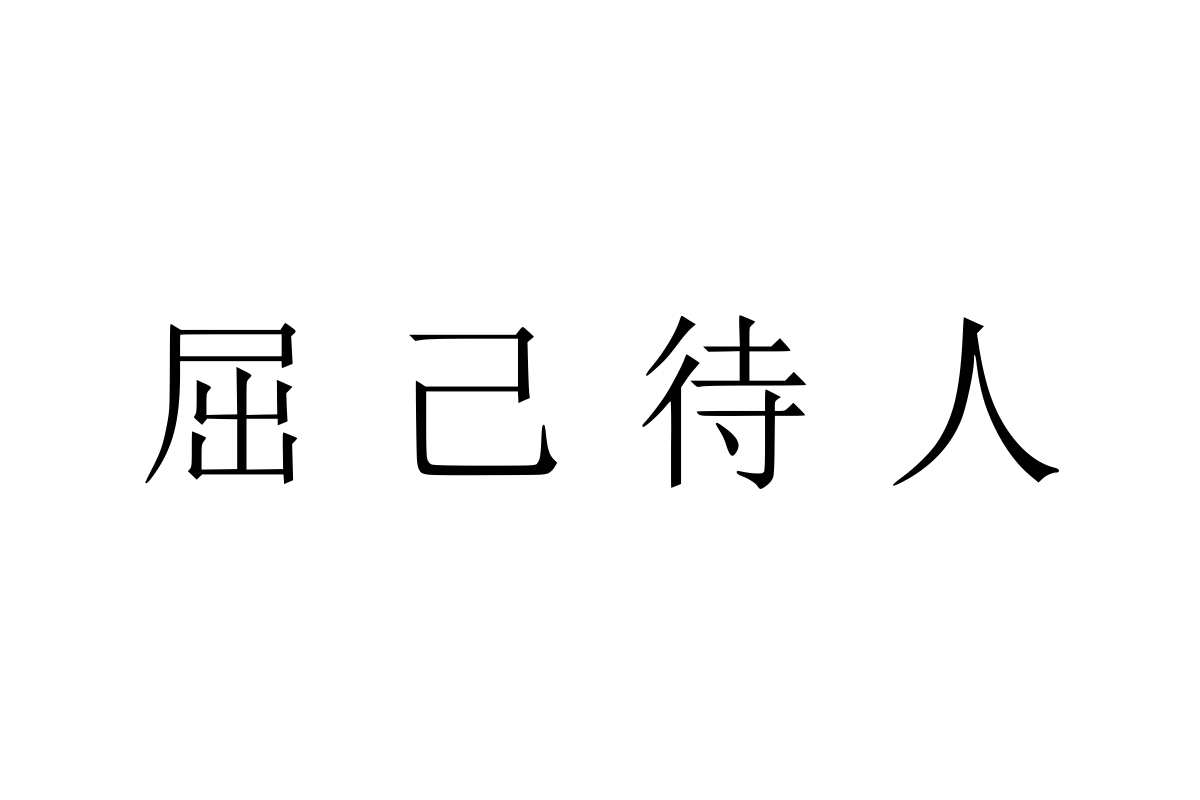
兰米新宋字体是一款具有现代感和艺术感的中文字体,它采用了独特的设计手法,将传统的宋体字与现代元素相结合。这款字体的特点是线条流畅、结构紧凑,给人一种简洁而不失美感的感觉。它的笔画粗细适中,既有力度又有柔美,适合用于各种需要书写或设计的场合。兰米新宋字体不仅适用于印刷品,也适用于电子屏幕显示,是一款非常实用的字体。